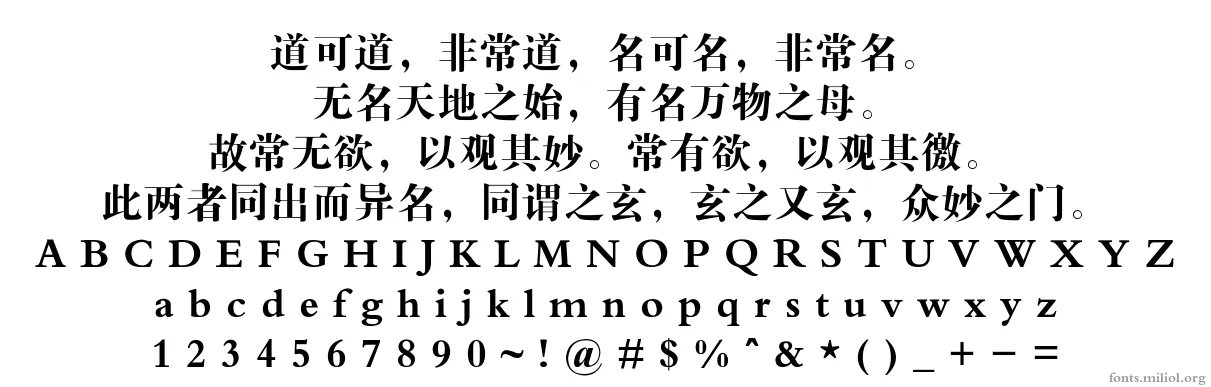
《方正大标宋_GBK字体:传统与现代的视觉融合》
方正大标宋_GBK(FZDaBiaoSong-B06)是一款兼具传统韵味与现代适用性的中文印刷字体,隶属于方正字库的经典GBK字符集系列。其设计以宋体为基底,笔画横平竖直,转折处棱角分明,整体风格庄重典雅,尤其适合标题、广告、书籍封面等需要突出视觉张力的场景。
作为GBK编码字体,方正大标宋支持超过两万个汉字字符,涵盖简体、繁体及生僻字,兼容性广泛,可满足跨地区、多场景的排版需求。其笔画粗细对比鲜明,结构严谨,在放大显示时仍能保持清晰锐利的边缘,避免了小字号下的模糊问题,特别适合大幅面印刷或数字屏幕的高清展示。
这款字体既延续了宋体的文化底蕴,又通过优化笔形细节增强了现代感,是政府文件、品牌宣传、文化出版物等领域的优选字体之一。其标准化的设计语言,确保了在不同媒介中的视觉统一性,为中文排版提供了兼具功能性与美学价值的解决方案。